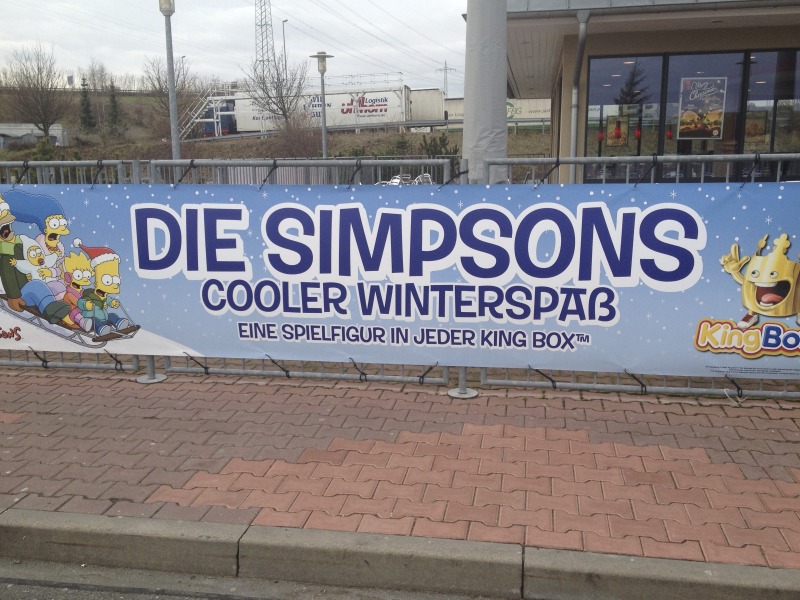
Stimmt. Ich glaube aber, dass Ralfs Intention einfach nur war, ein alternatives Formenprinzip für die Gestaltung des Buchstabens aufzuzeigen, das auch für Gestalter von Antiquaschriften inspirierend sein könnte.
Das ist mir an sich klar, ich habe trotzdem die Gelegenheit ergriffen, anhand des Beispiels auf den Umstand hinweisen, daß die Frage nach einem Versal-ß sich bei vielen Schriften, die eben keinesfalls für Versalsatz benutzt werden sollten, gar nicht stellen muß.
ich habe mich bei der beschriftung für etiketten gerade gegen das versal-ß entschieden (das aus der skolar) weils einfach blöd aussah und störend wirkte. ich habe den begriff einfach gemischt geschrieben, jetzt muss es nur noch der kunde abnicken. ist ein redesign, vorher stand da ein SS.
Bin aber auch als ẞ-Verfechter ganz bei dir: man soll es nicht um des ẞ selbst willen einsetzen. Wenn’s (aktuell) nicht funktioniert, muss man es auch nicht erzwingen.
Ich finde die Idee des Schmucks gut, lustige Vorführung, aber verlinkt hatte ich die Seite, weil das Fehlen eines versalen ß dort so wehtut wie kaum irgendwo. Man vermißt es doch gerade in der schönen SCHEIßE schmerzlich, nicht?
Da hast Du natürlich recht! Ich habe mich beim Betrachten der Seite gefragt, ob die schmerzhaft-falsche Verwendung des ß als Sahnehäubchen auf der Basisabsurdität dieses ganzen Projektes gezielt eingesetzt wurde, oder ob Herr Schamoni dann doch zur Gruppe der ẞ-Ahnungslosen gehört …? Eigentlich würde ich ersterer Annahme zuneigen.
Sahnehäubchen auf so was? Ich finde dieses sprachliche Bild, hüstel, fragwürdig. Sahne! Häubchen! Aber eine beabsichtigte Steigerung von Scheiße mag es vielleicht tatsächlich sein. Es sticht ja doch arg ins Auge. (Sprachliche Bilder sind in diesem Zusammenhang wirklich heiße Kartoffeln.)